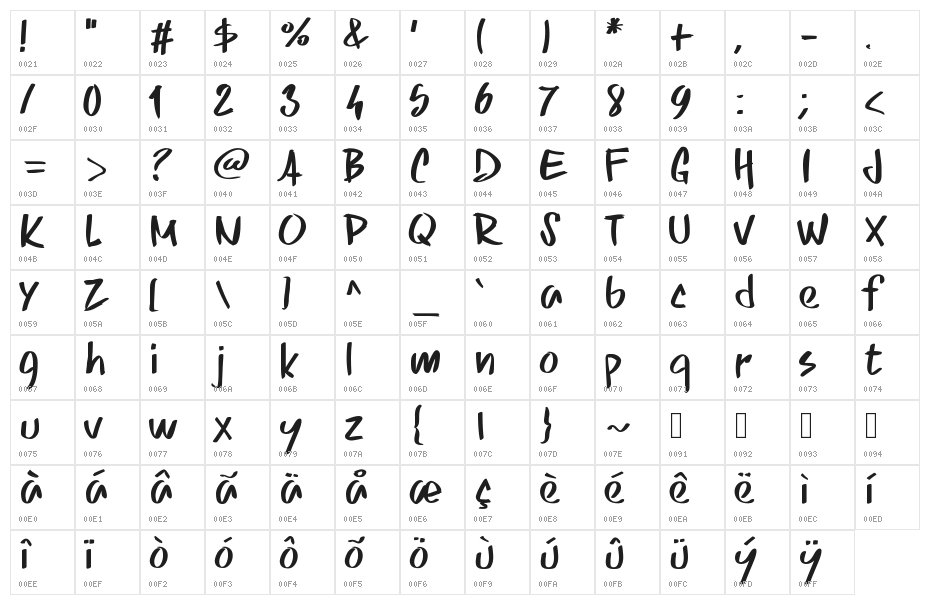
PWSkriptt Font
| Stile generale | Modern, Artistic |
| Caso d'uso | Headlines, Logos, Creative projects |
| Progetti proposti | Ideal for greeting cards, posters, branding, and social media graphics where a personal and artistic touch is desired. |